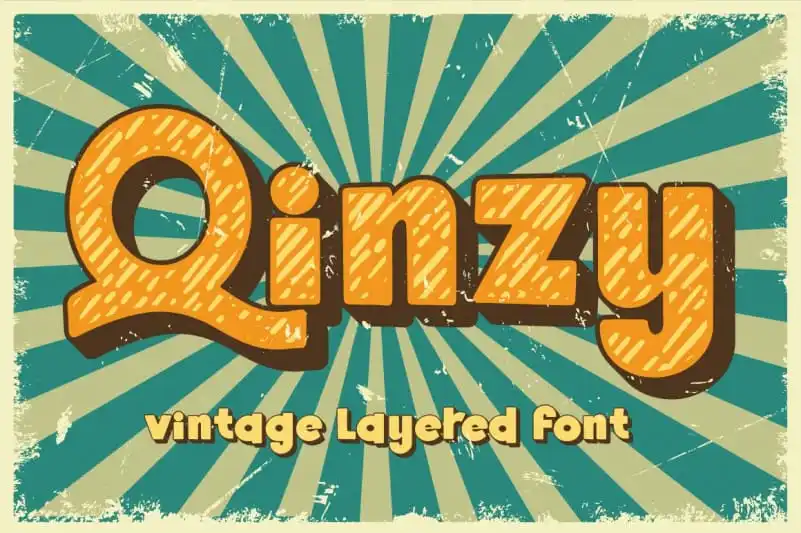
A Qinzy Display Font é uma escolha perfeita para quem busca um estilo sofisticado e contemporâneo sem perder a influência vintage dos anos 70. Inspirada nas tipografias de época, a Qinzy oferece três estilos diferentes da família do tipo, garantindo tanto versatilidade quanto a facilidade na criação de efeitos tridimensionais. Seu design, cuidadosamente concebido pela Attype Studio, é ideal para gráficos de destaque ou texturas em websites. Com seu modernismo clássico, a Qinzy Display é uma fonte perfeita para ambientes digitais que valorizam tanto o atual quanto o histórico. Ela oferece um contraponto elegante aos desafios contemporâneos, enquanto ressalta as influências do passado através de sua herança tipográfica retrô. Com a Qinzy Display Font, você pode transformar qualquer layout digital em uma arte visual vibrante e sofisticada que combina perfeitamente a modernidade com o encanto da nostalgia.